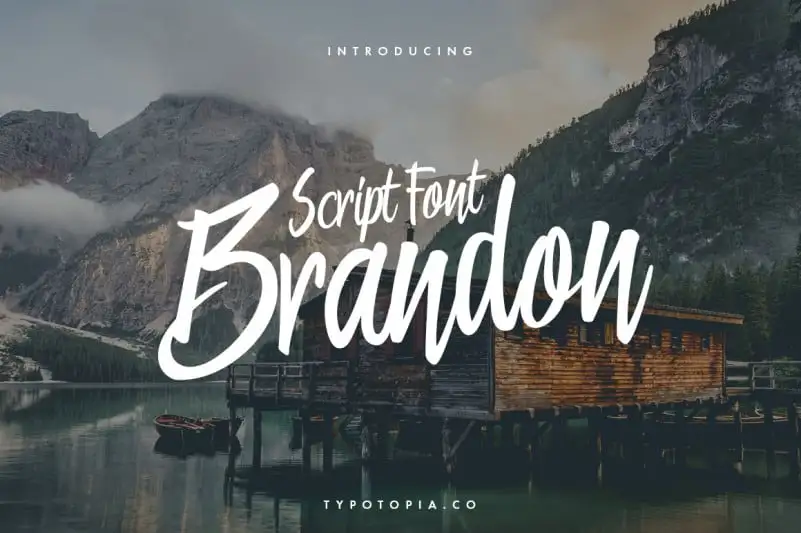
Brandon Script Font – Fonte Grátis
Brandon Script Font
A “Brandon Script Font” é uma deliciosa tipografia script, envolventemente suave e ondulada. Ela possui uma linha base que flutua modernamente como calligrafia, criando um look perfeitamente autoral. Perfeita para designers de projetos, essa fonte pode ser combinada de forma equilibrada para manter o look elegante e fluido. Os ligadíferos, números e uma variedade de símbolos tornam a “Brandon Script Font” um recurso indispensável para qualquer designer que procura dar um toque delicado e autêntico em suas criações digitais. O design da typotopia oferece tanto sofisticação quanto versatilidade, com um equilíbrio perfeito entre modernidade e tradicionalismo.